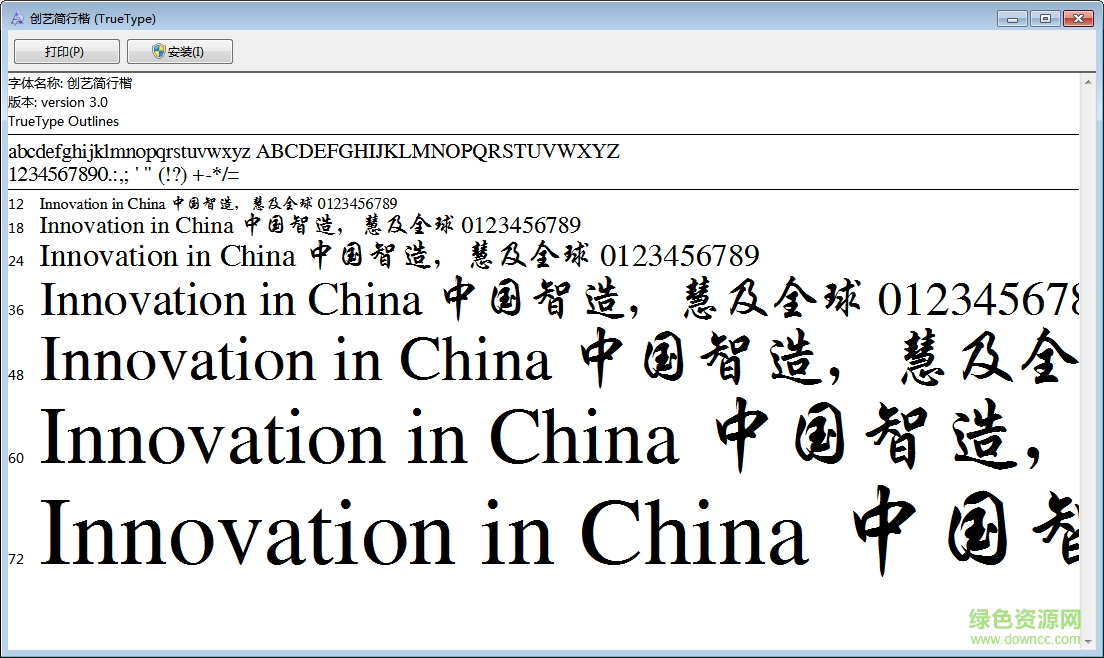
創(chuàng)藝簡行楷字體是一款非常好看的創(chuàng)藝字體,字體筆畫瀟灑,非常的舒展,字體整體偏粗,非常的醒目,適合用于廣告設(shè)計(jì)和包裝印刷行業(yè),歡迎有需要的朋友到綠色資源網(wǎng)下載使用吧!
字體飄逸灑脫,行筆流暢自然,剛勁舒展,書法韻味濃,適用于書籍、報(bào)刊、雜志的標(biāo)題字和宣傳、裝飾用字。